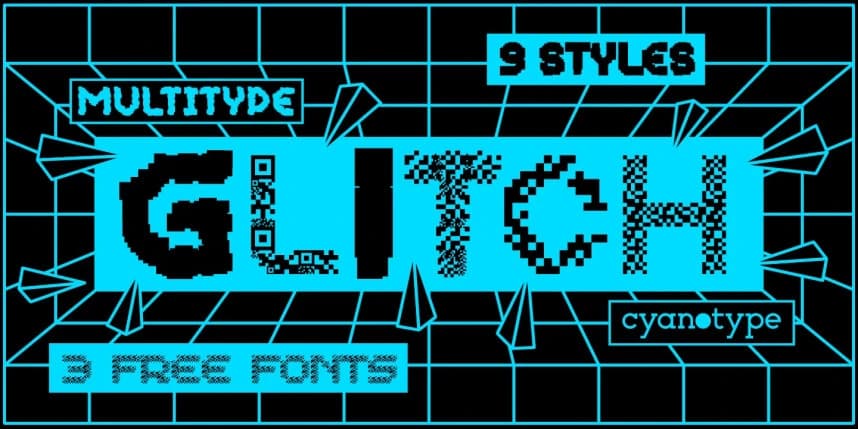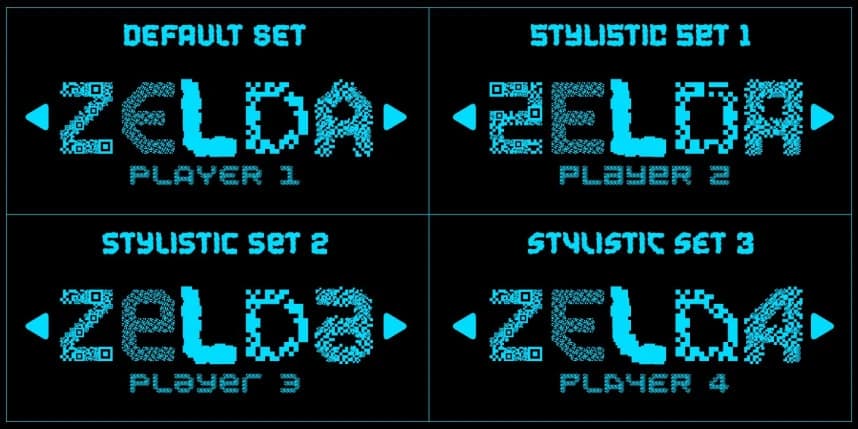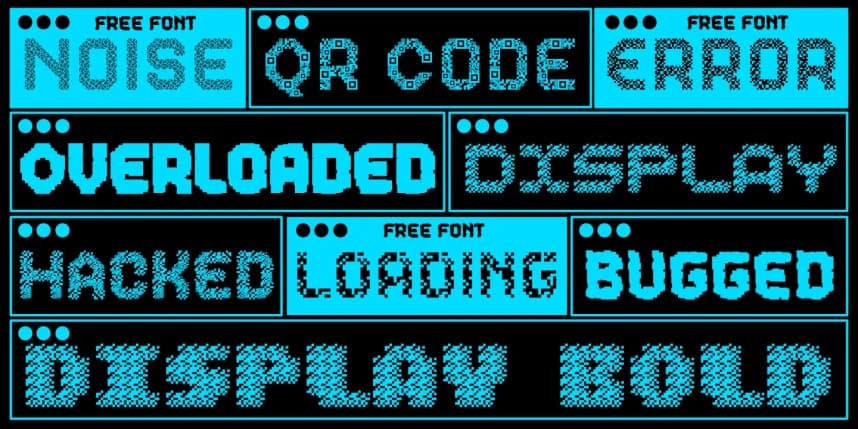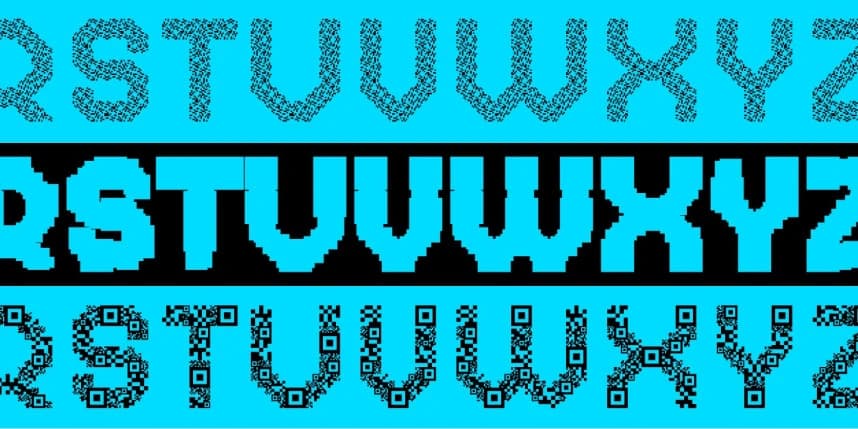
MultiType Glitch Font
MultiType Glitch Font, sergileme amaçları için odaklanmış, tamamen büyük harflerden oluşan bir yazı tipidir. Glitch görünümlü 9 stile sahip. Bu, genişleyen ve birbirleriyle karıştırılabilir fontlardan oluşan çok evrenin üçüncü sürümüdür. Tüm yazı tipi ailesi, büyük boyutlarda ve marka oluşturma gibi
MultiType Glitch
MultiType Glitch Error
MultiType Glitch Loading
MultiType Glitch Noise